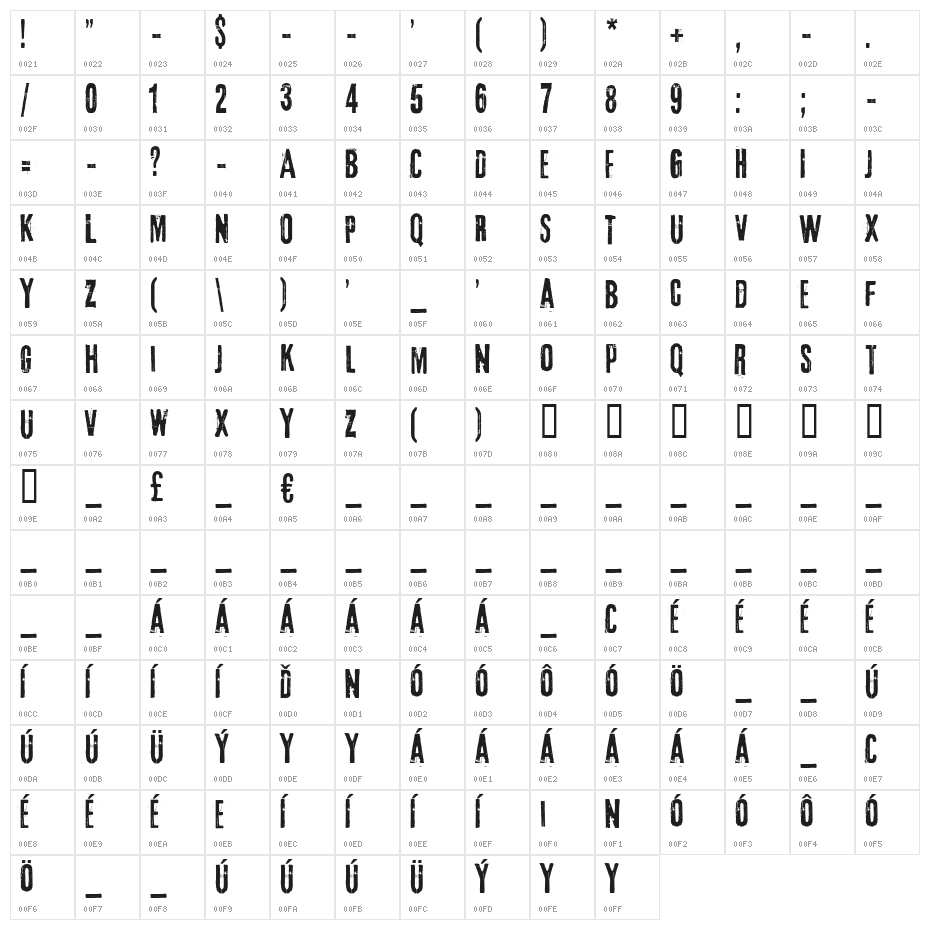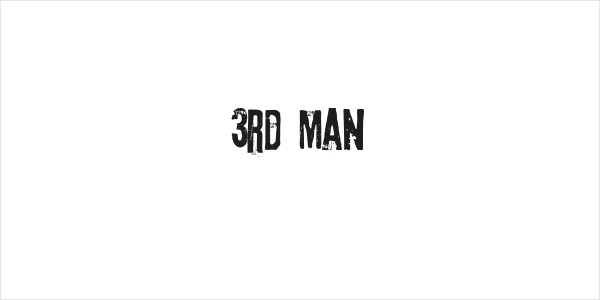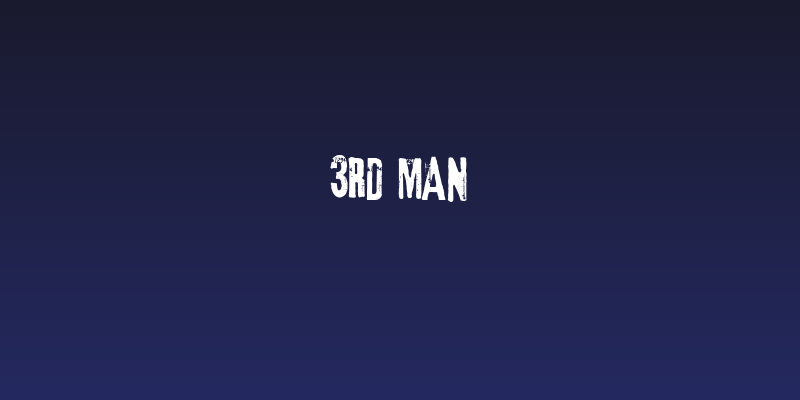
3rd Man Font
✎ Distorted Eroded
| Progetti proposti | Perfect for poster designs, album covers, branding for rugged products, and any project needing a vintage or industrial touch. |